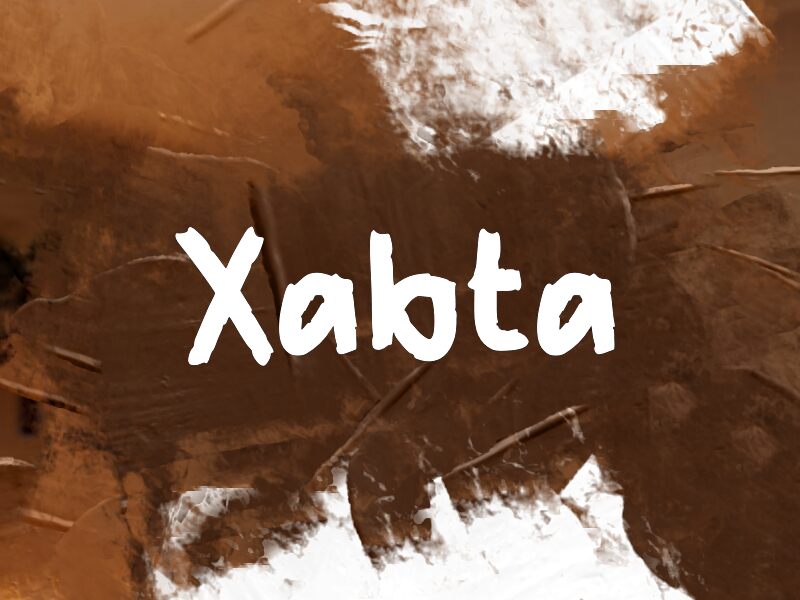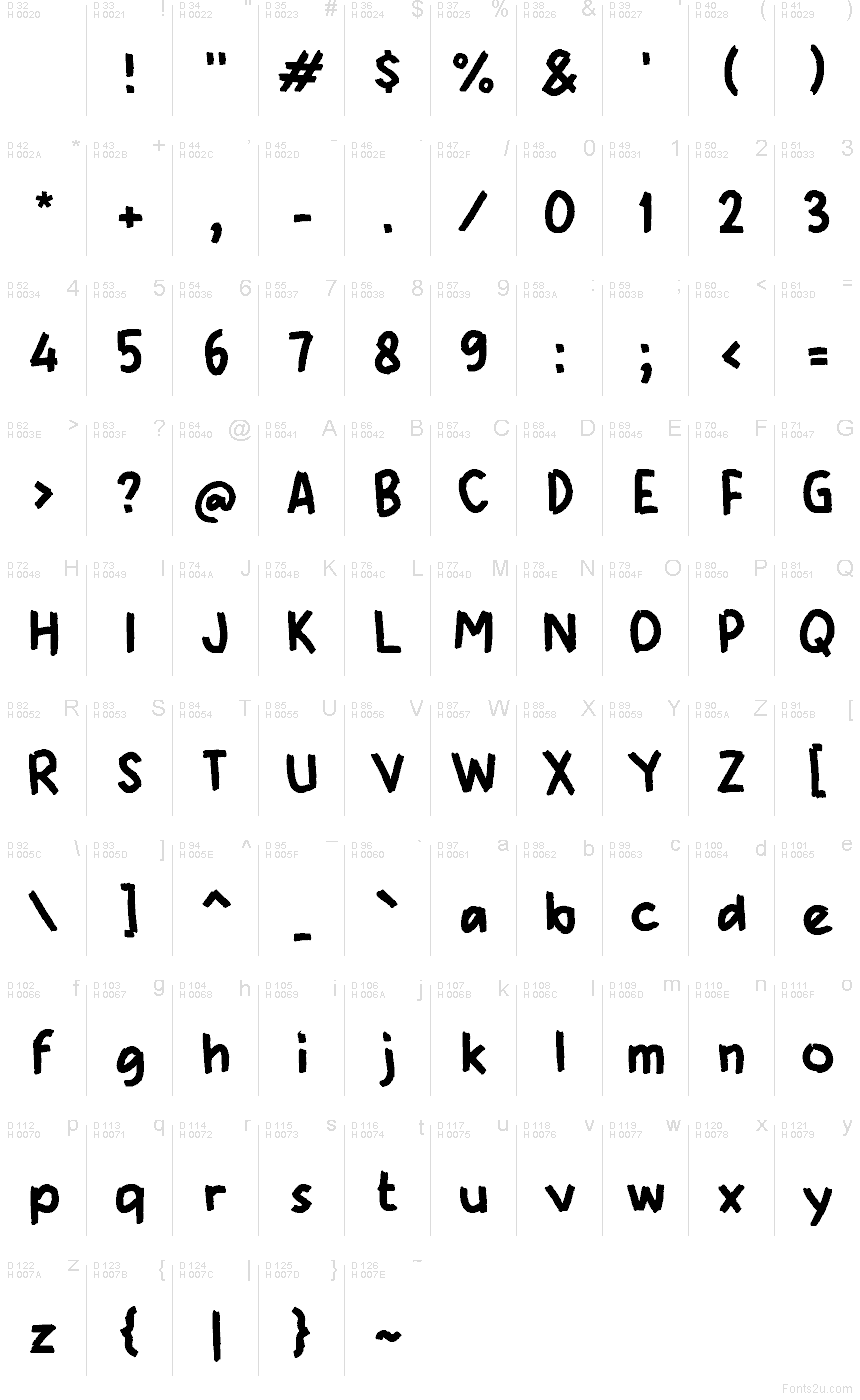
Xabta
Xabta di Wep è un font brush gratuito dallo stile grezzo e dipinto a mano. Le lettere sembrano tracciate con un pennello carico: tratti spessi e irregolari, una lieve oscillazione e giunzioni corpose le conferiscono il ritmo autentico di un’insegna dipinta, ben lontano da una calligrafia levigata.
È perfetto per flyer musicali, grafiche streetwear, titoli di poster, packaging e locandine dove un font gratuito deve avere spessore e un tocco umano. Poiché i tratti sono ampi e un po' vissuti, Xabta dà il meglio di sé su parole brevi, nomi e titoli che possono valorizzare la sua texture granulosa e materica.